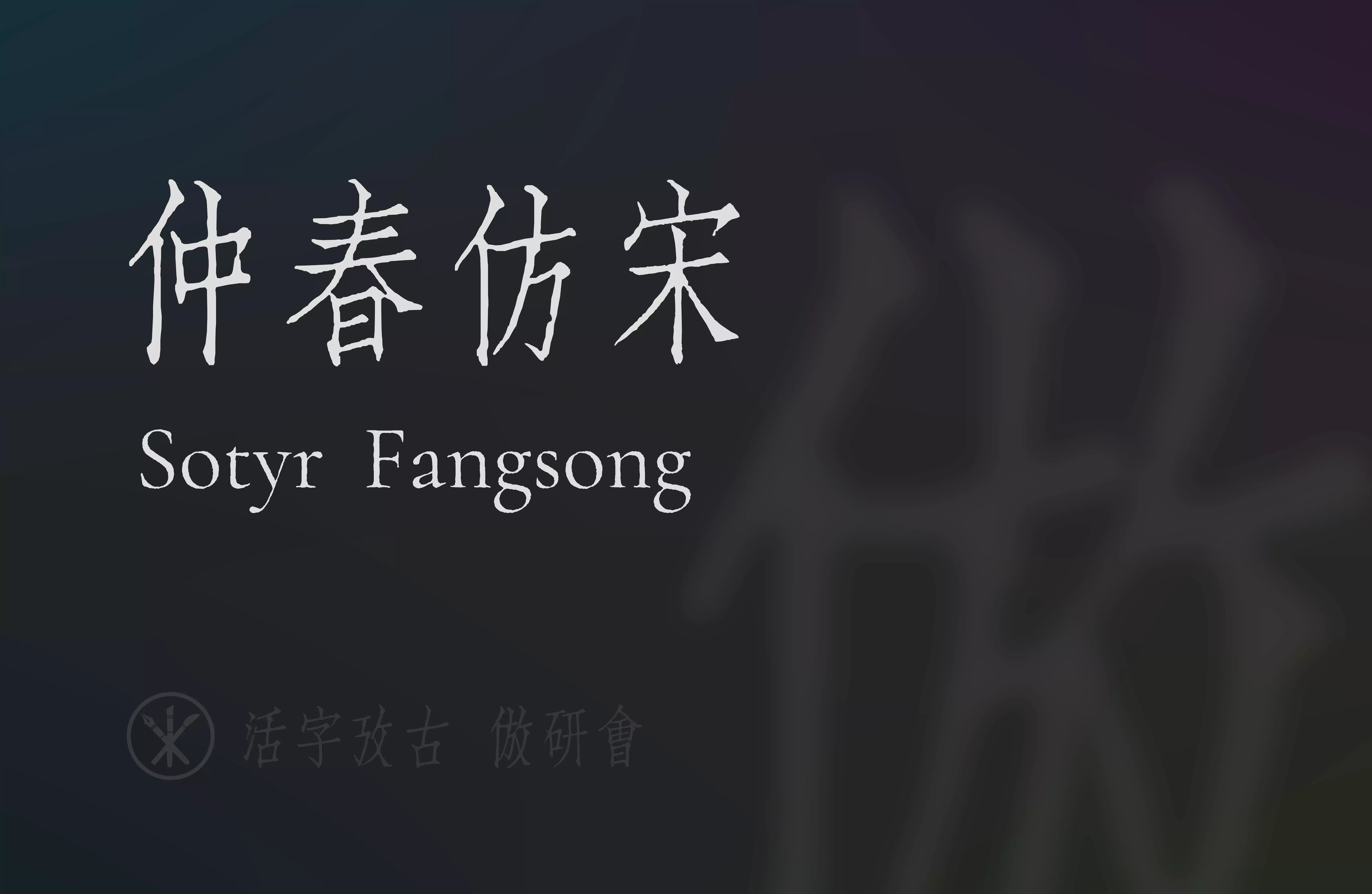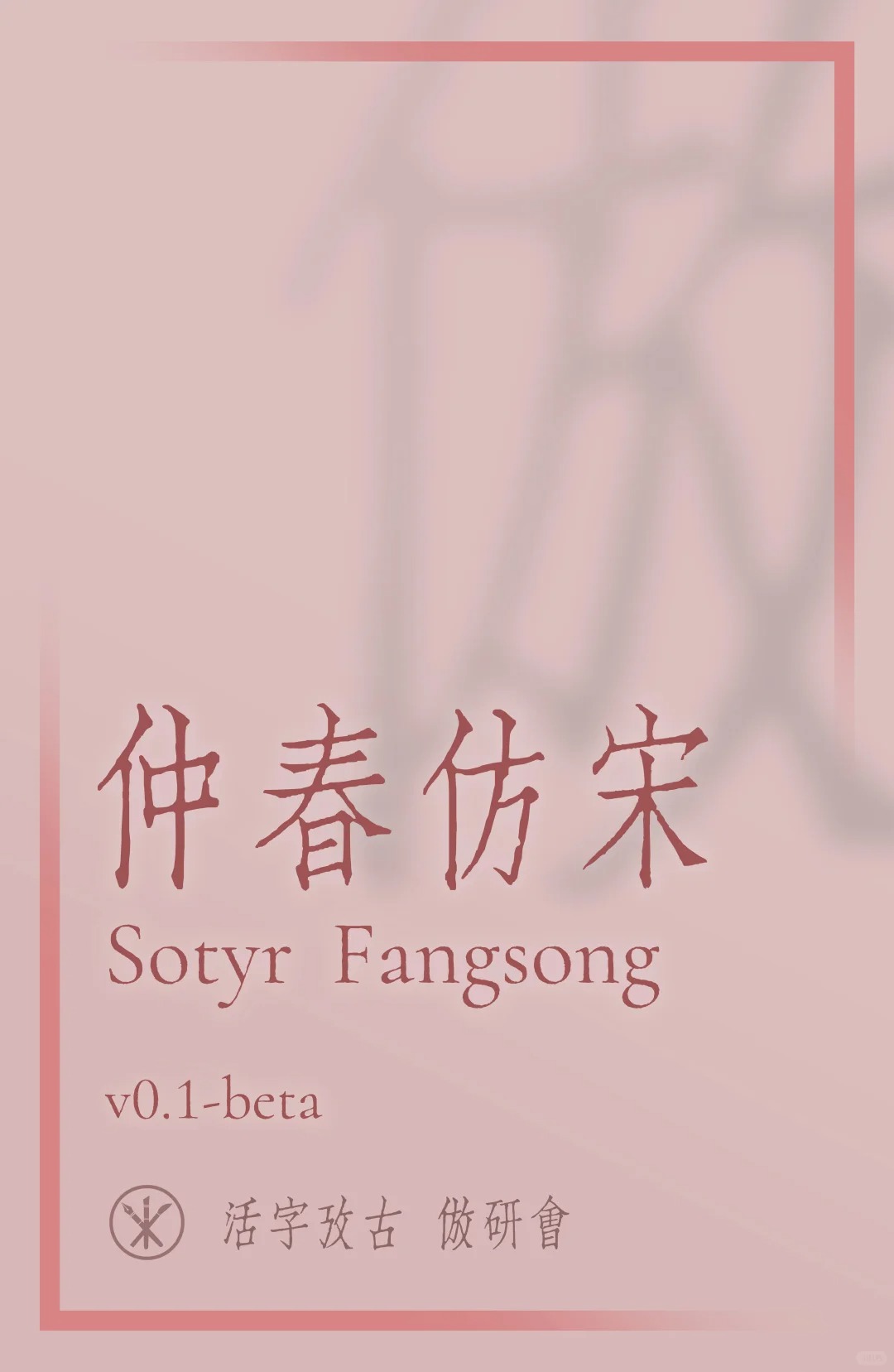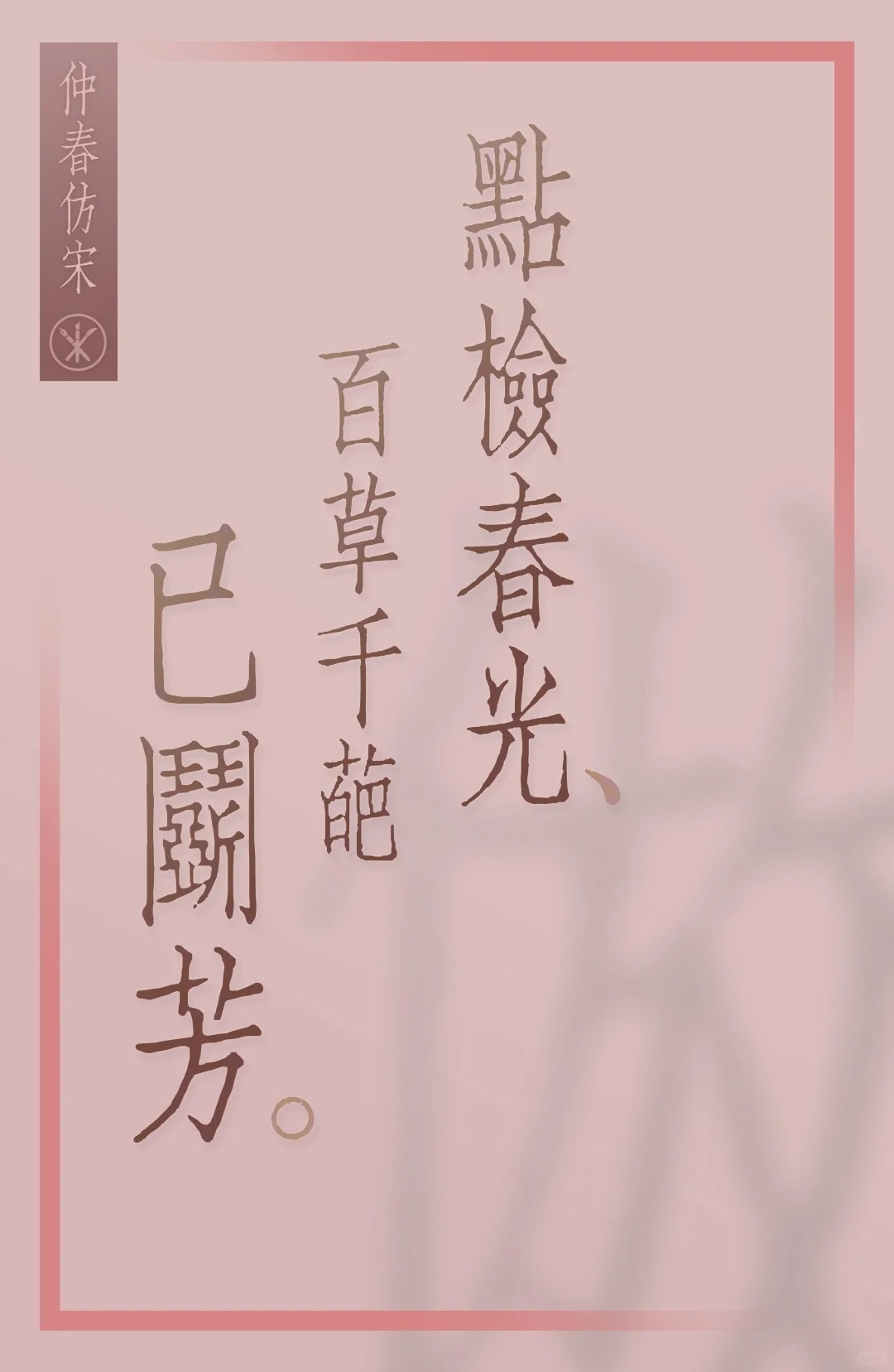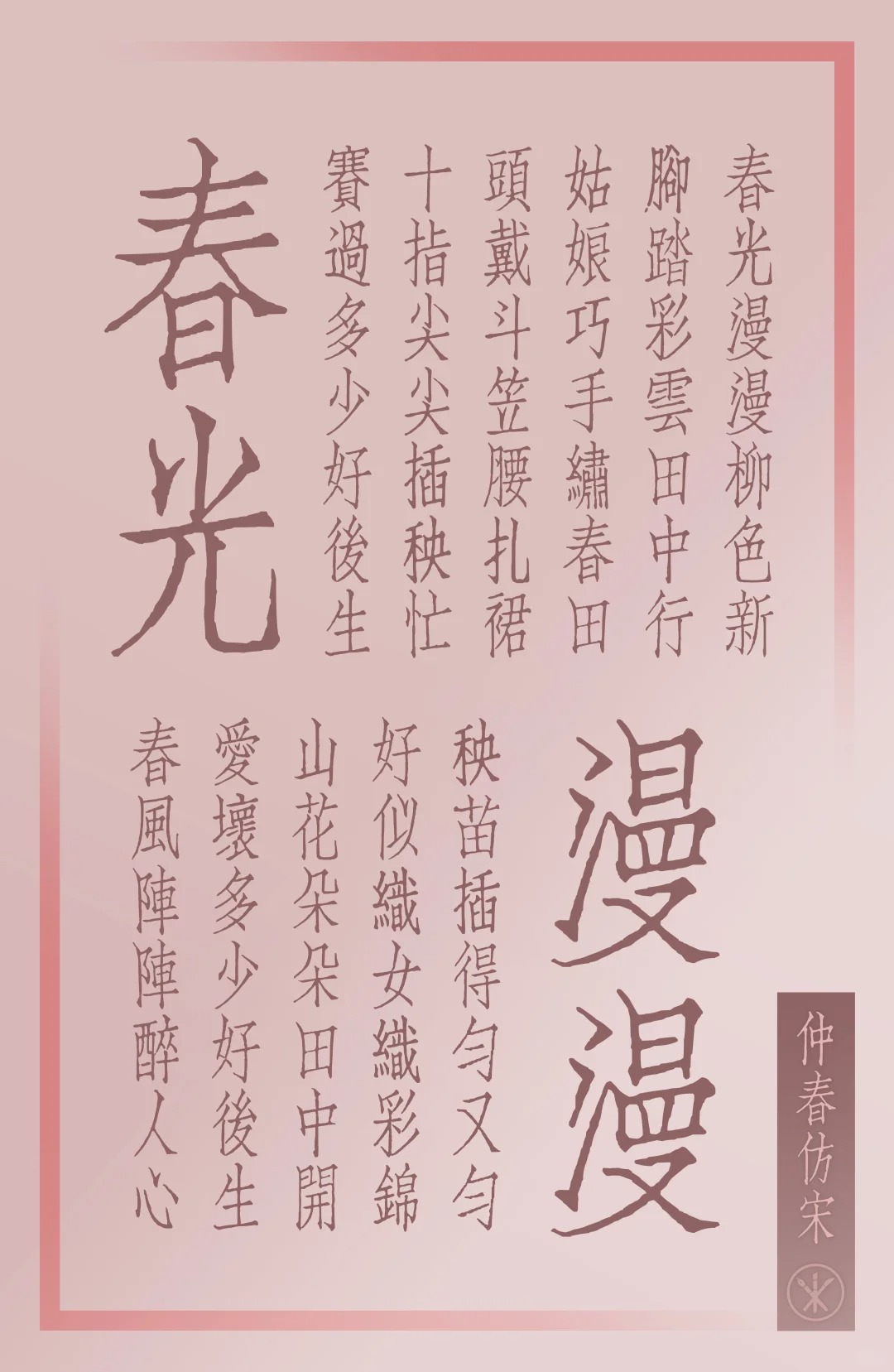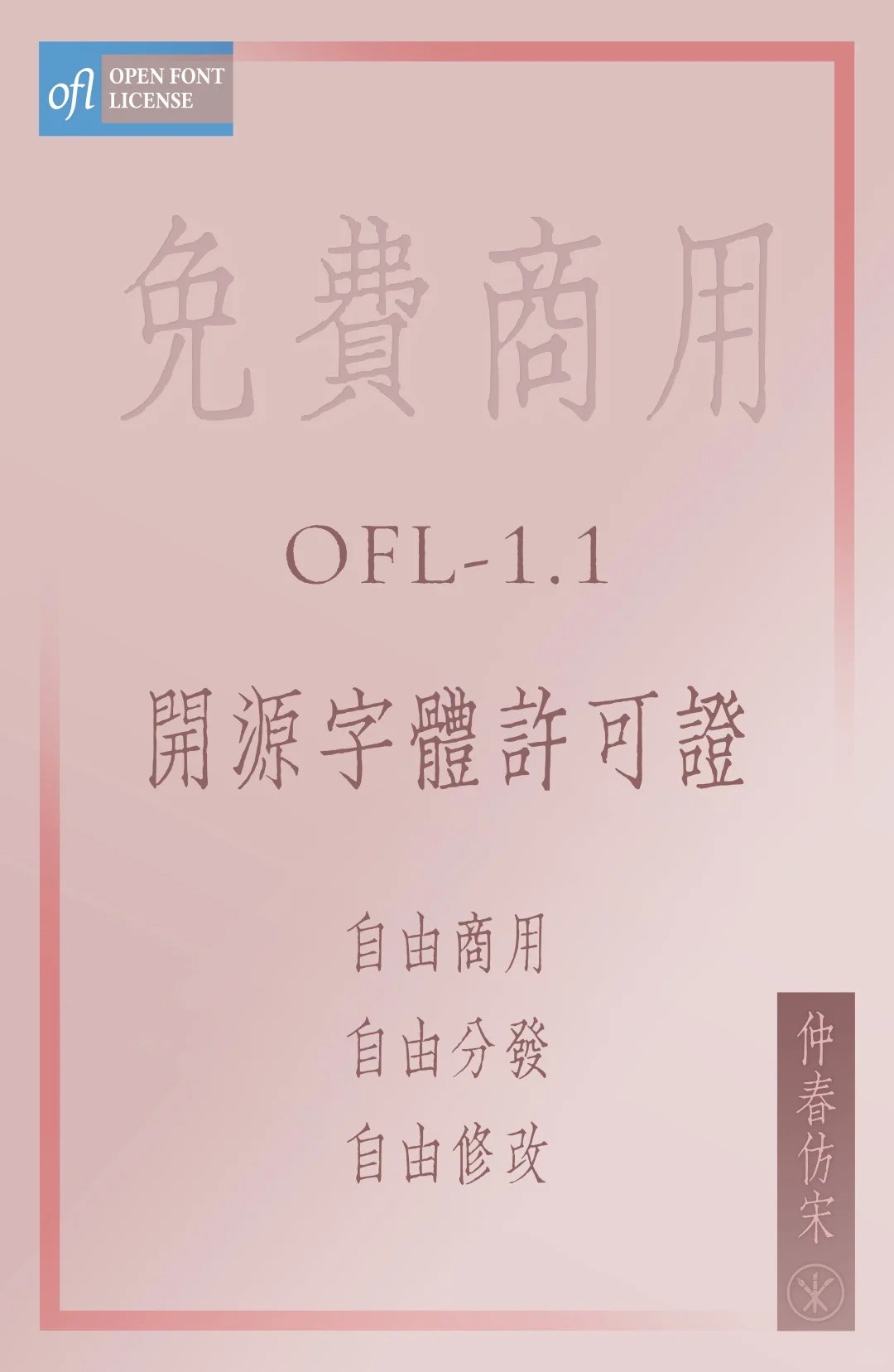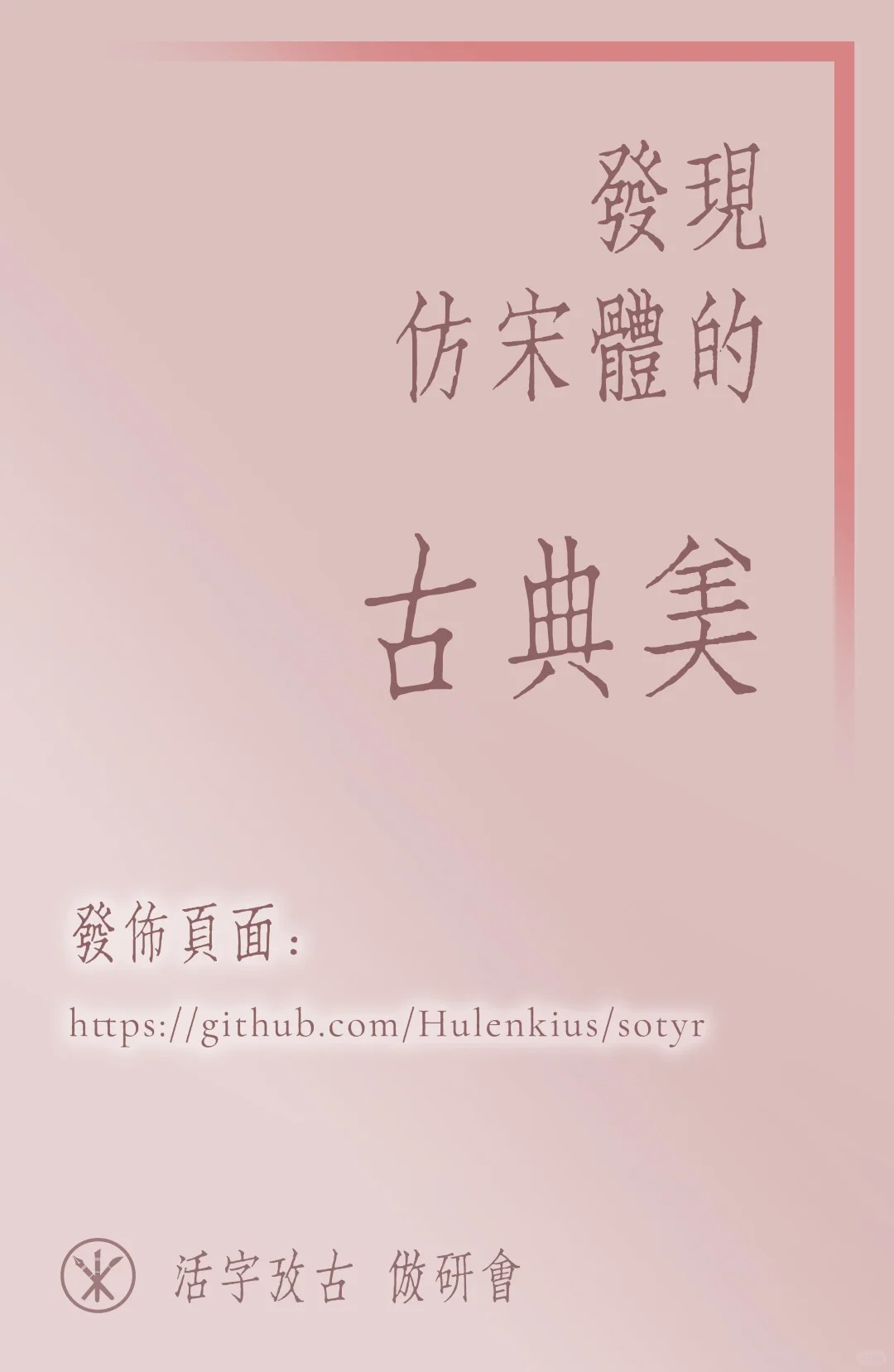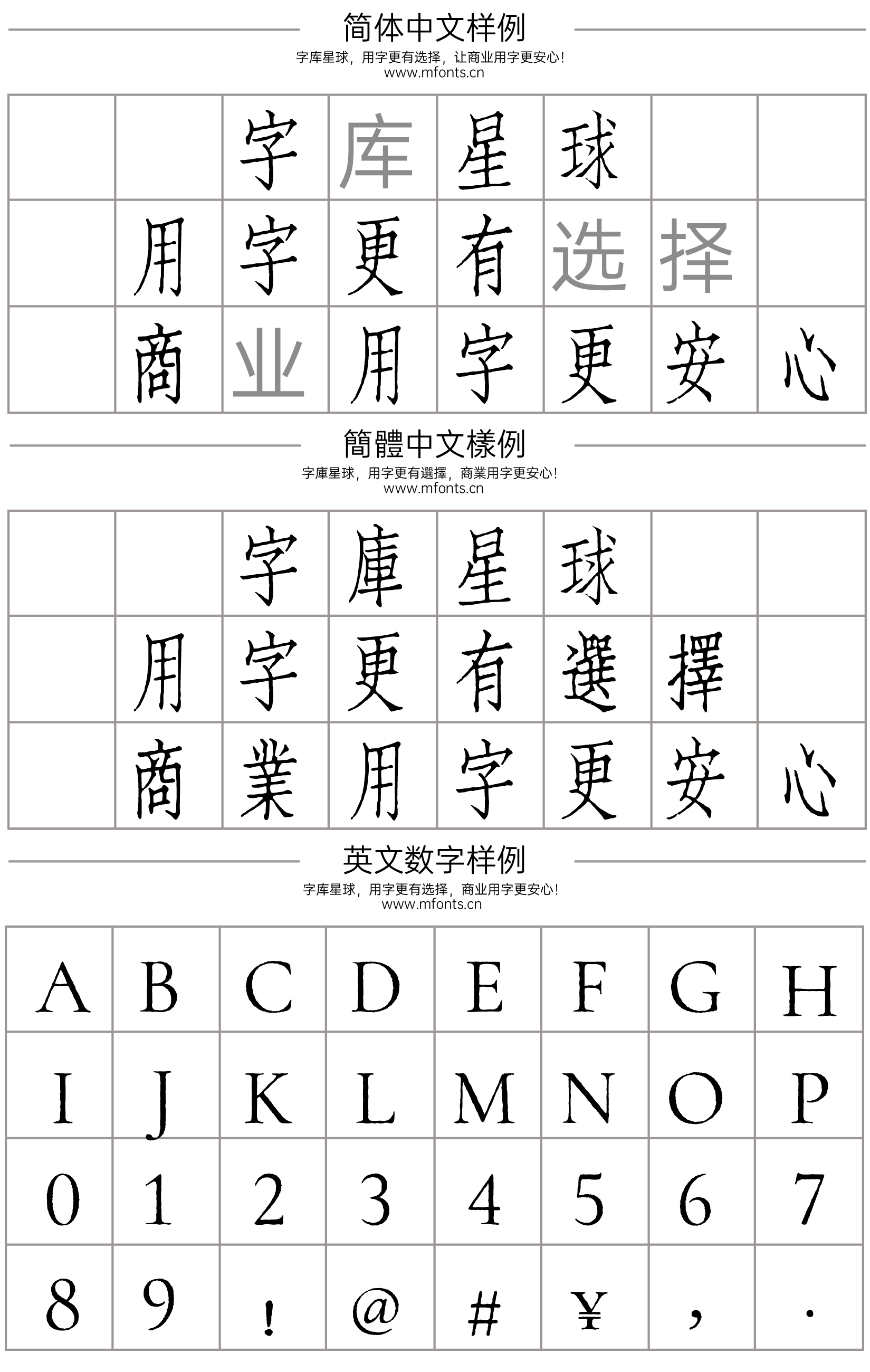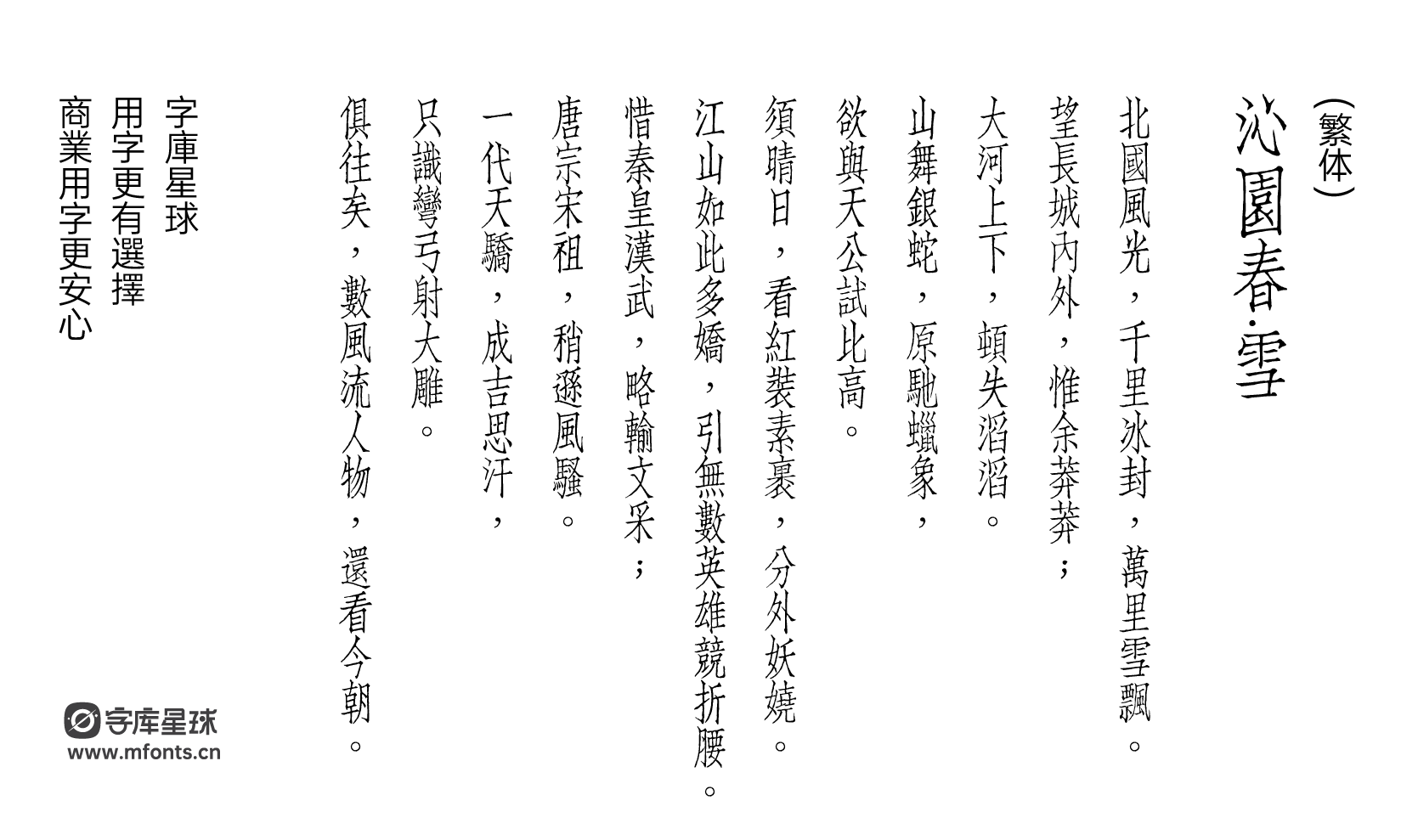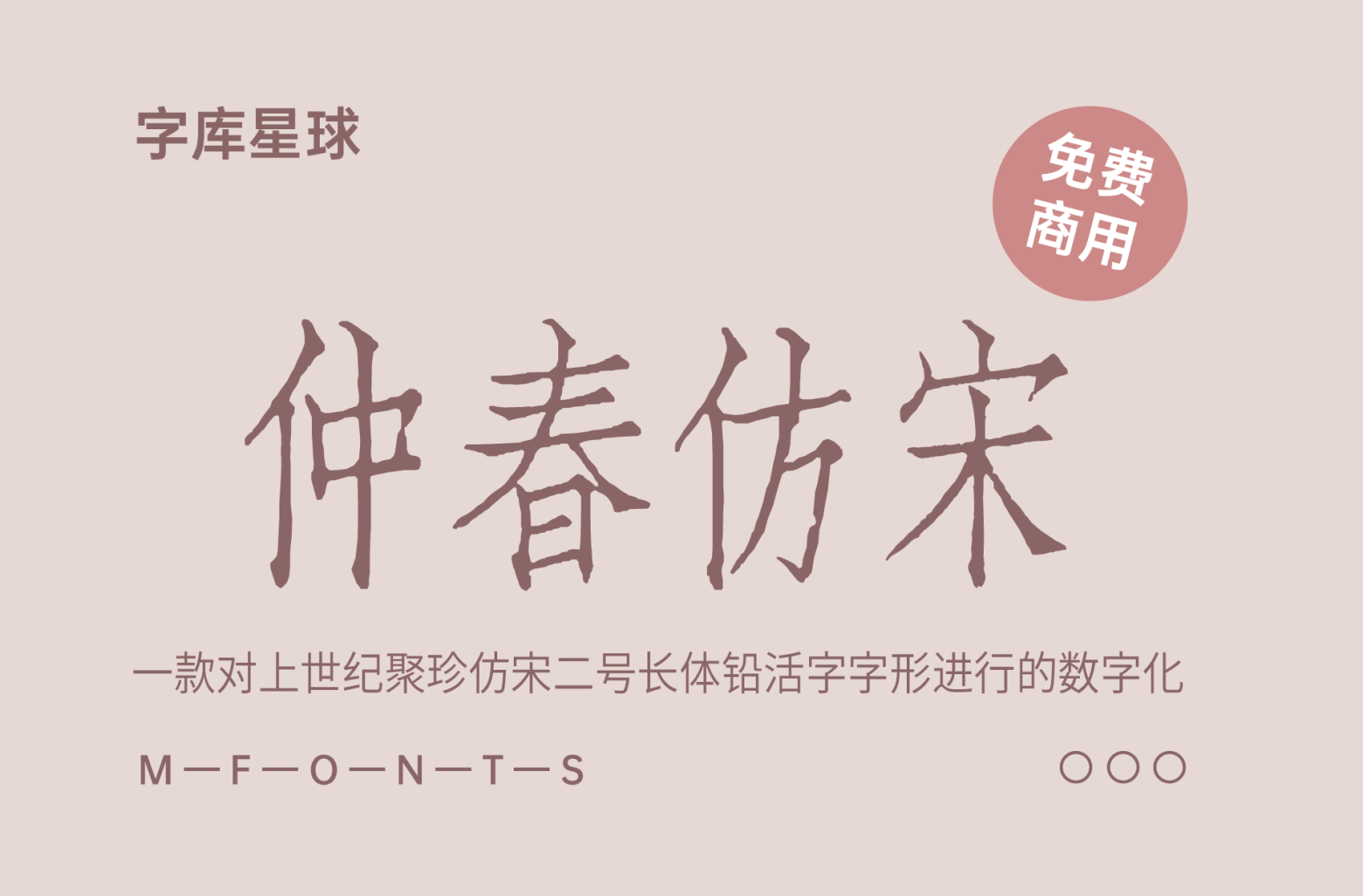
仲春仿宋是一款对上世纪聚珍仿宋二号长体铅活字字形进行的数字化。采用直接复刻办法,从印刷品扫描件中提取字形并封装为字体。
项目尚处于开发和测试阶段,其中的缺字、丑字不少,远不及正式版发布的程度。简化字部分是基本没有的,也不太推荐用于现代汉语文本的排版,还请各界朋友多多包涵。
开发故事
若论哪套长体仿宋最为著名?熟谙近现代印刷史的同志,恐怕大都会脱口而出「聚珍仿宋」。不过聚珍仿宋的长体铅字自身又包含多种字号,哪一种最具代表性?这个问题的答案或许在同志们的脑海中能浮现出,但落实到具体字号层面,就不那么好回答了。
聚珍仿宋二号长体铅字,造型妍美多姿,而又因其字号适中,常应用于正文排版而不是标题和夹注。相比于头号字的直健、三号四号字的间架异化处理、五号字的细密,二号字的字形可以说是最丰富地展现了聚珍仿宋家族的风味。同时,上世纪末,聚珍仿宋二号长体经过史云鹏的大力推广,成为了工程类制图常用的手写体。工科出身的朋友们,你们当年有没有练习过呢?
聚珍的头号方体长体、二号方体,市面已有产品,而尚无二号长体产品可用。
在印刷品样本方面,现在开放的电子化扫描件非常多了,缺少的只是对其中的字形进行提取封装的工作。这个工作量不小,所以从今年(2025)1 月开始,我们又合作开发了一种切片工具和一种封装前处理工具,效率大为提升,小组内的同志们拊掌称奇。
总之,「仲春仿宋」是传统汉字美学、印刷和数字化技术、新生产力结合的产物。
问:「为什么要叫『仲春』」呢?
答:这个项目是乙巳年仲春开始进行的。此外「仲」有「排行第二」的意思,而「春」的声符「屯」又有「聚集」的意思;二者结合,与「聚珍二号」暗应。「Sotyr」是「聚珍」的谐声域。
文章标题:仲春仿宋